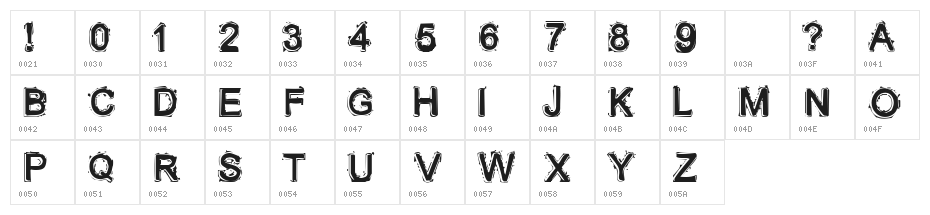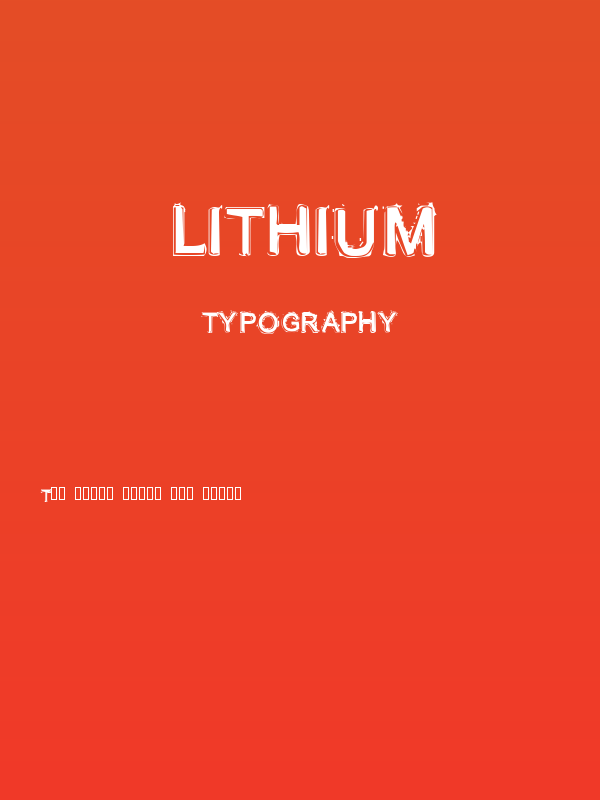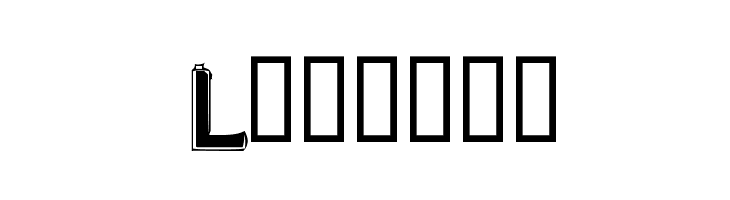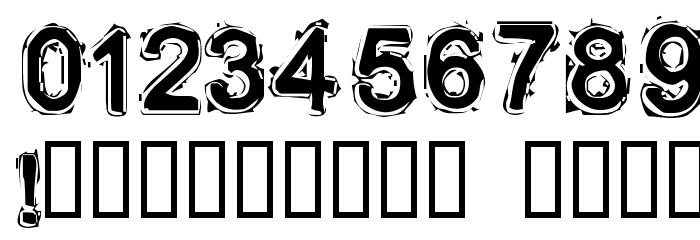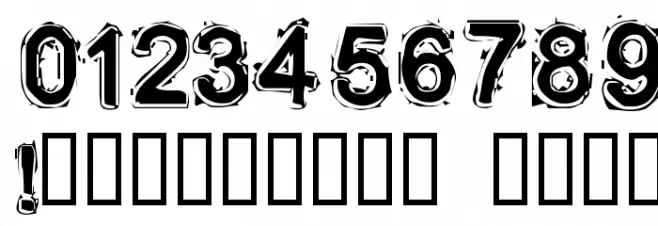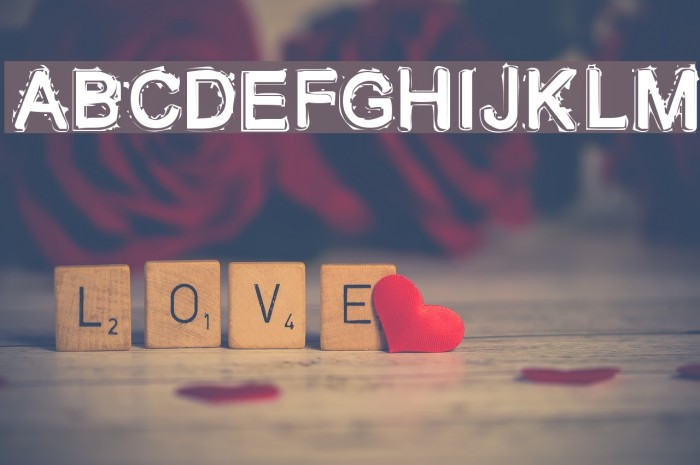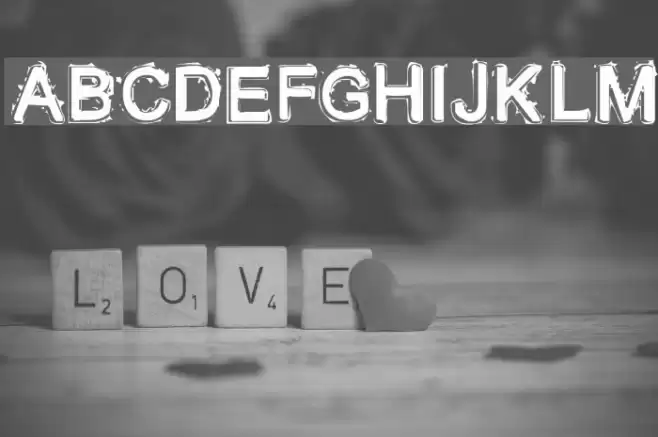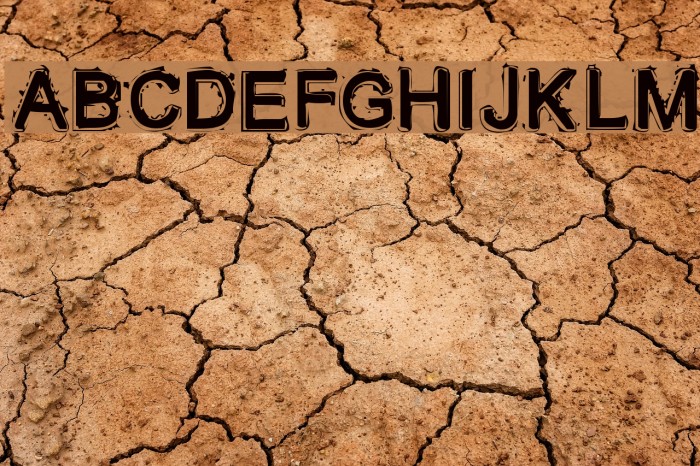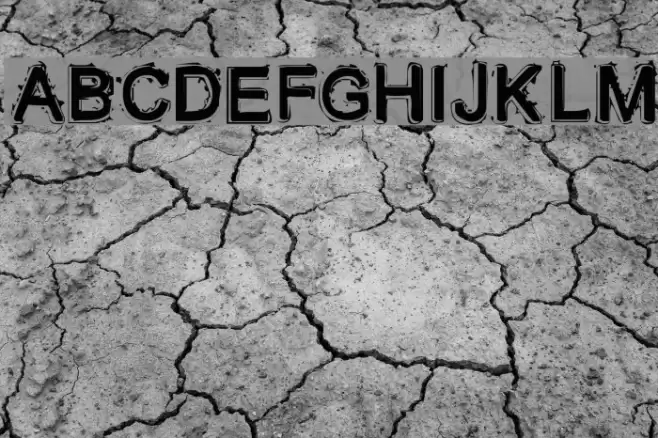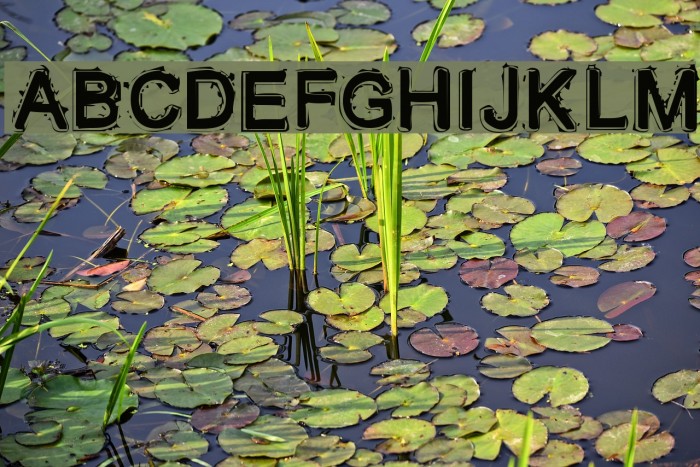
Lithium Font
| Anwendungsfall | Logos, Headlines, Posters |
| Vorgeschlagene Projekte | Ideal for music album covers, posters, urban-themed branding, and any project needing a bold, artistic flair. |